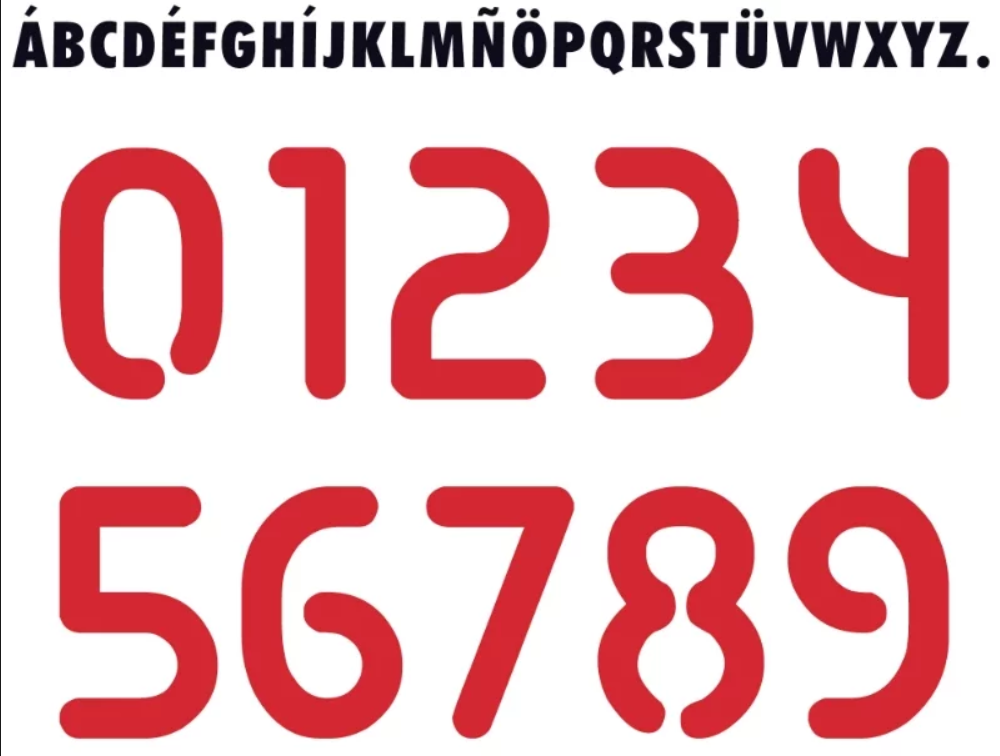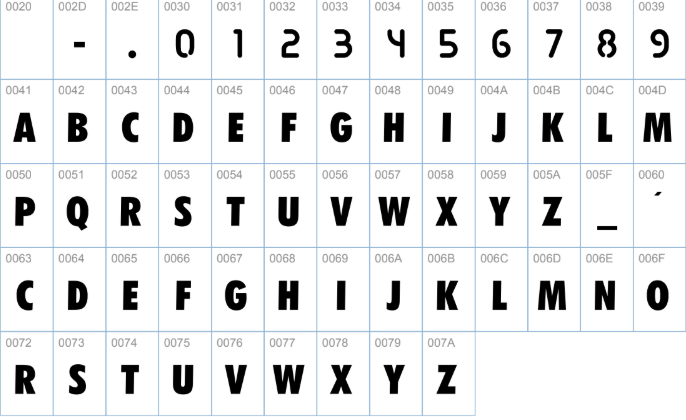
Se você é designer, publicitário ou simplesmente um torcedor apaixonado pelo São Paulo FC, sabe que a tipografia de uma camisa conta uma história. O ano de 2013 marcou uma fase importante para o clube, que vestia uniformes icônicos fornecidos pela Penalty. A fonte usada naquela temporada para nomes e números tem uma identidade visual única, e agora ela pode ser sua.
Reviva os momentos daquela era em seus projetos gráficos. Esta é a fonte exata que estampou as costas de ídolos do Morumbi naquele ano.
Estilo e Identidade Visual
A fonte do São Paulo de 2013, desenvolvida pela Penalty, destaca-se por seu visual robusto e moderno. Ela possui traços firmes e cantos levemente arredondados, o que garante excelente legibilidade tanto de perto quanto à distância (essencial para a leitura em campo). Não é uma fonte agressiva; ela transmite solidez e clareza, alinhando-se perfeitamente aos uniformes tradicionais do clube, seja na camisa branca, na listrada ou nos uniformes de goleiro.